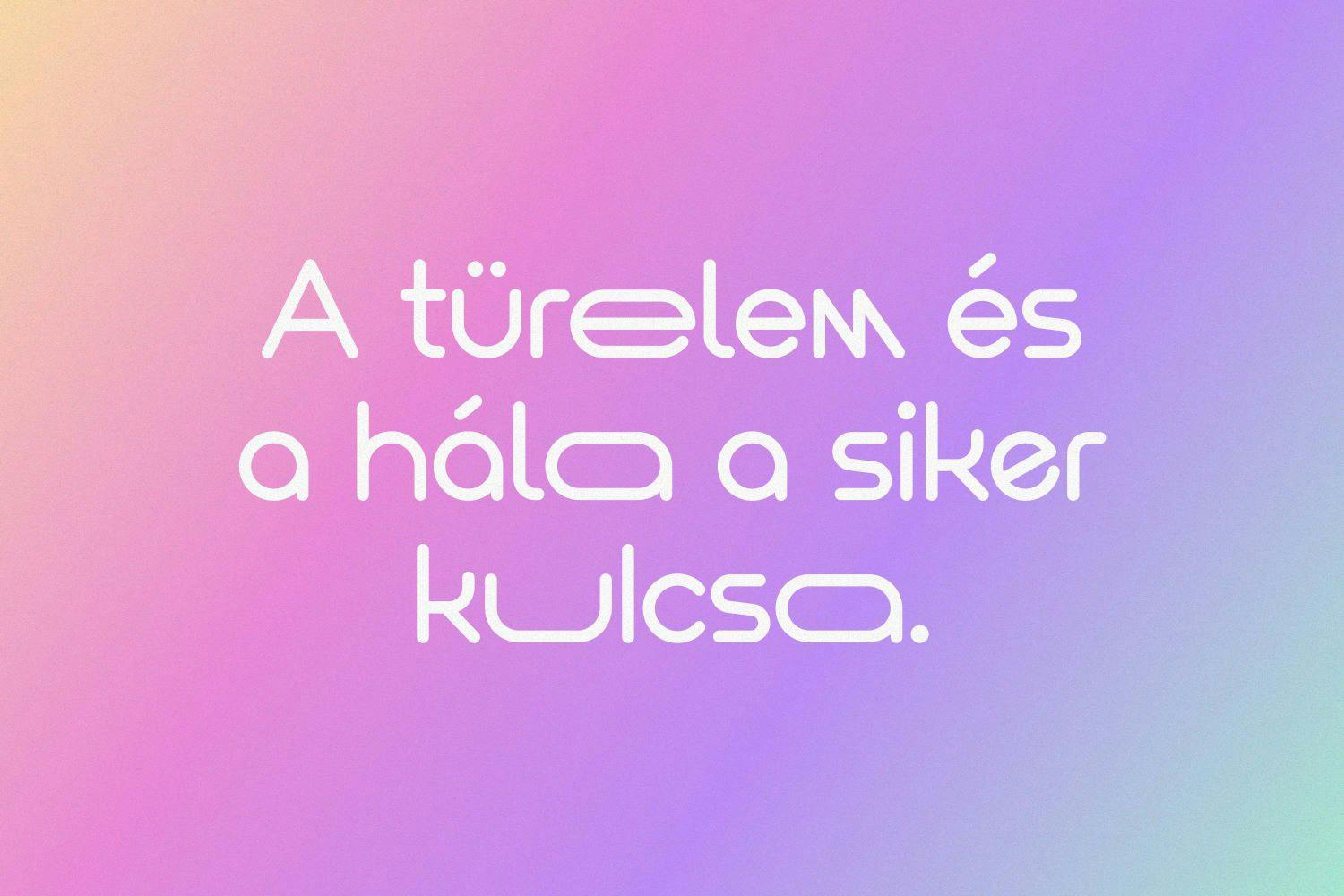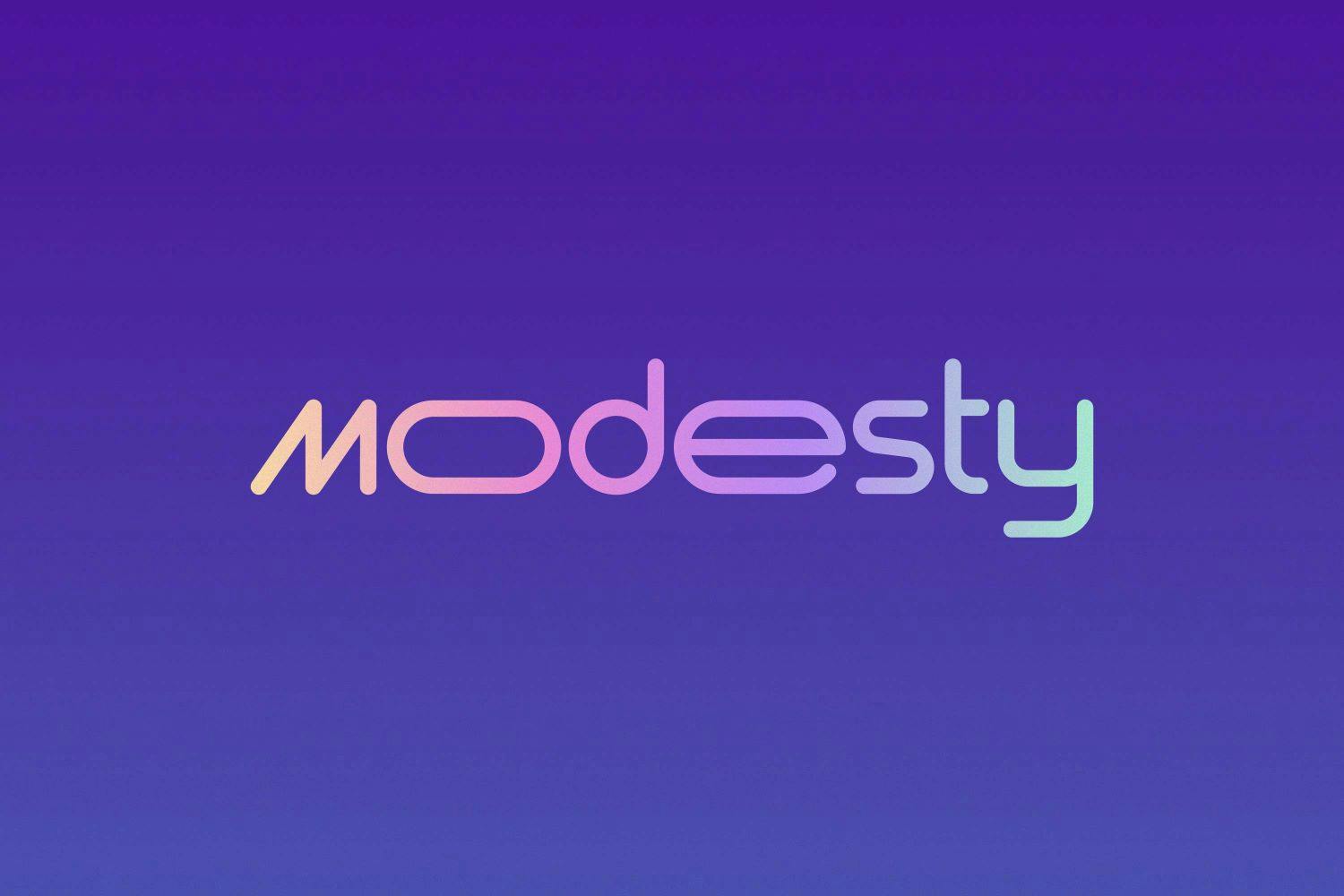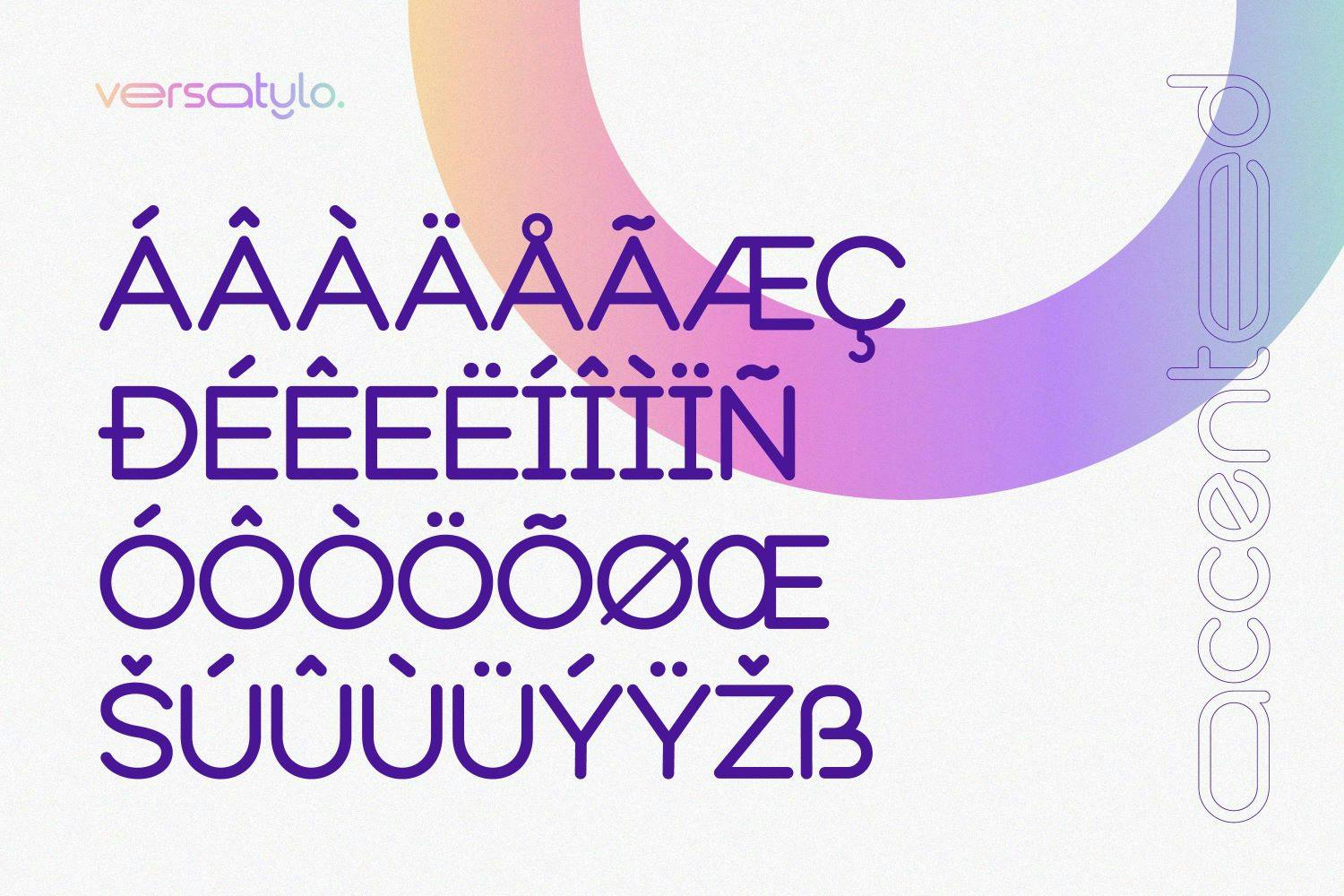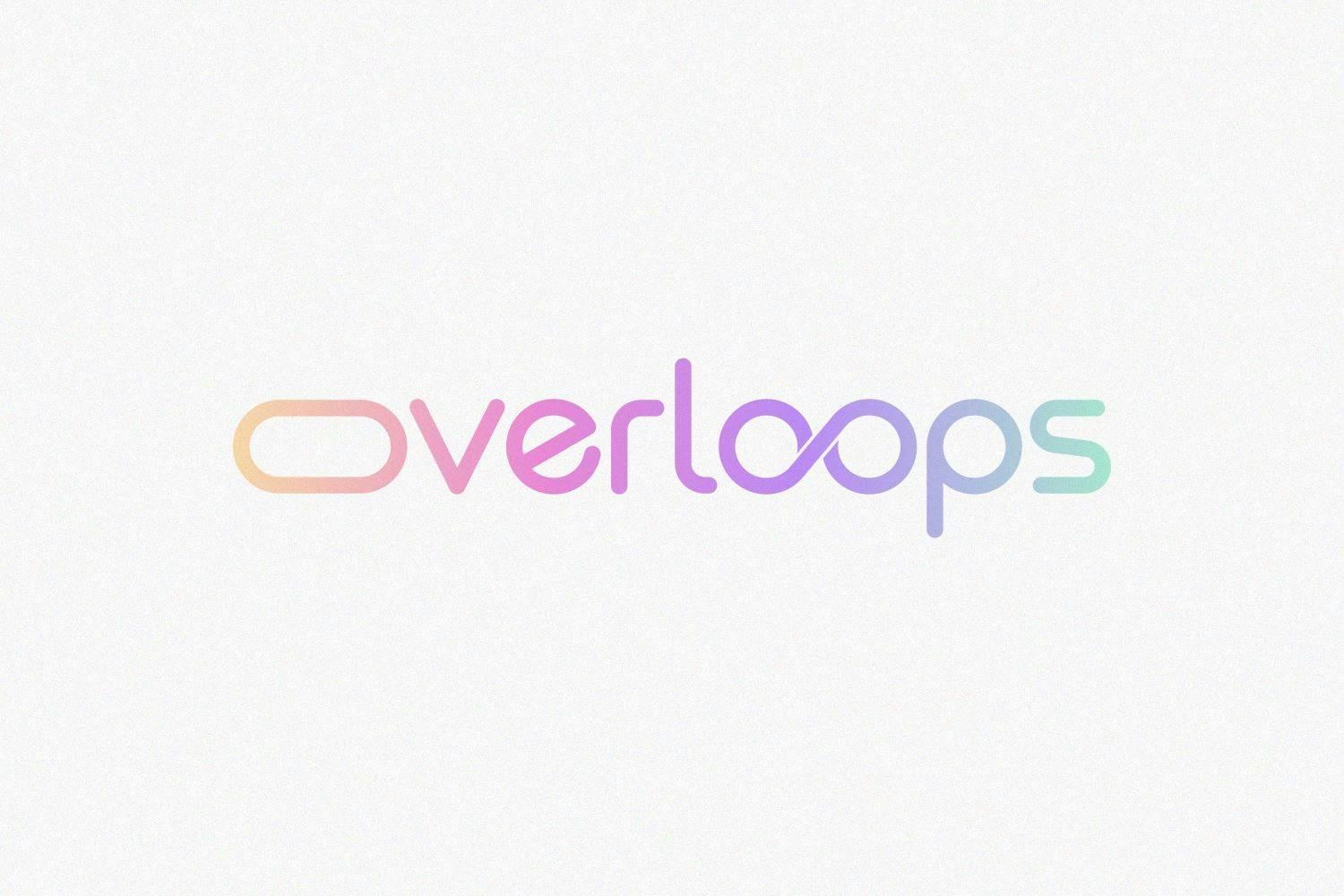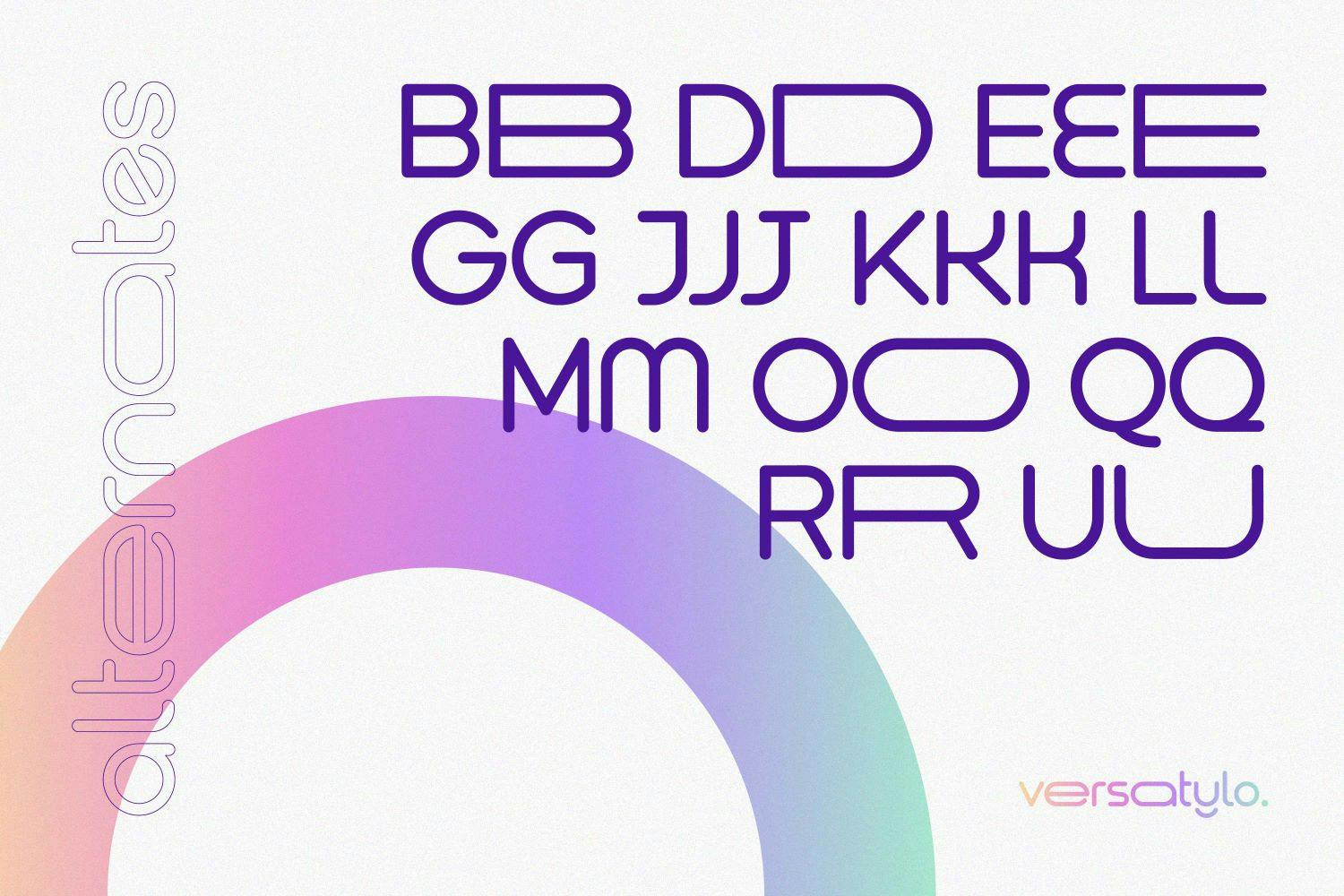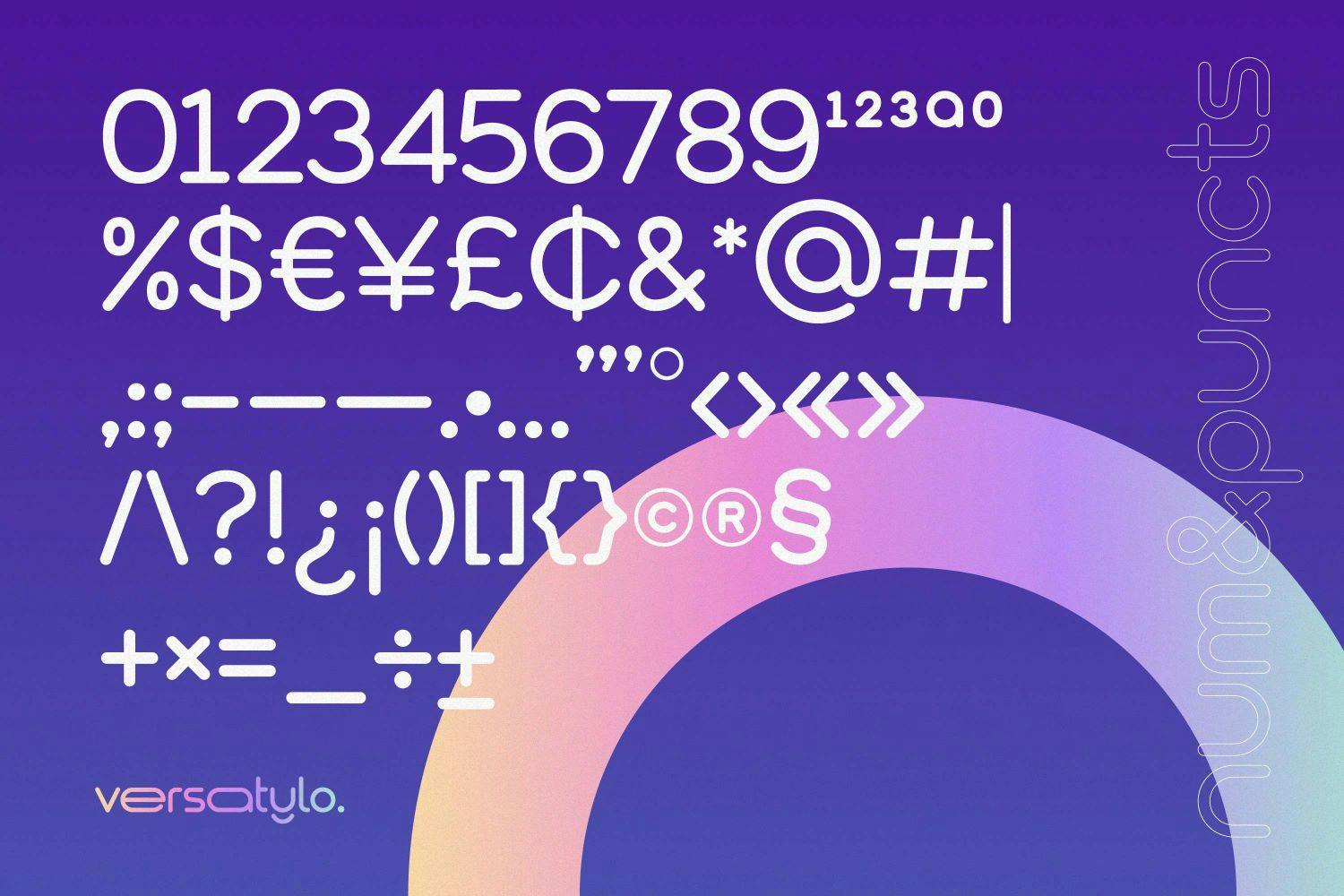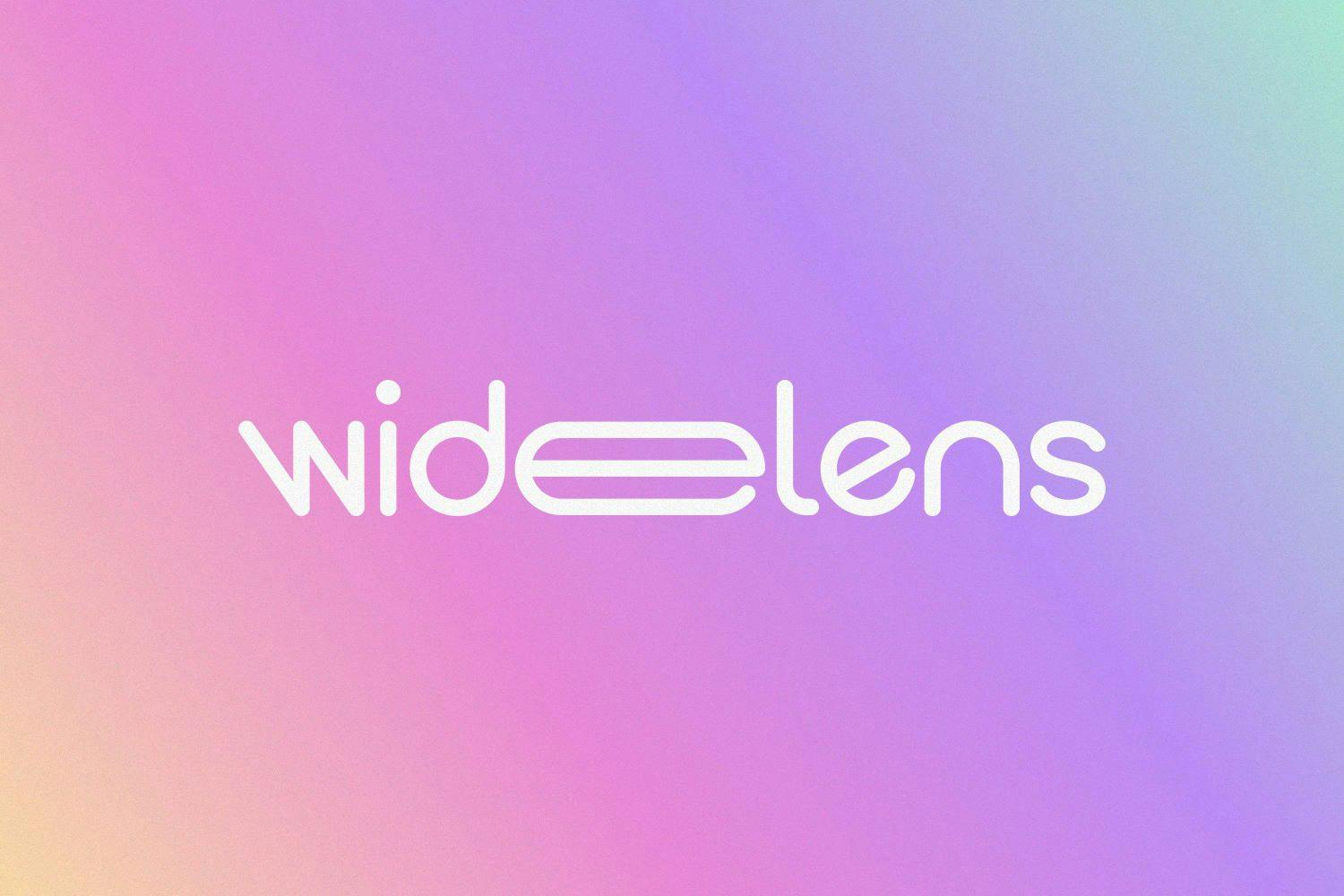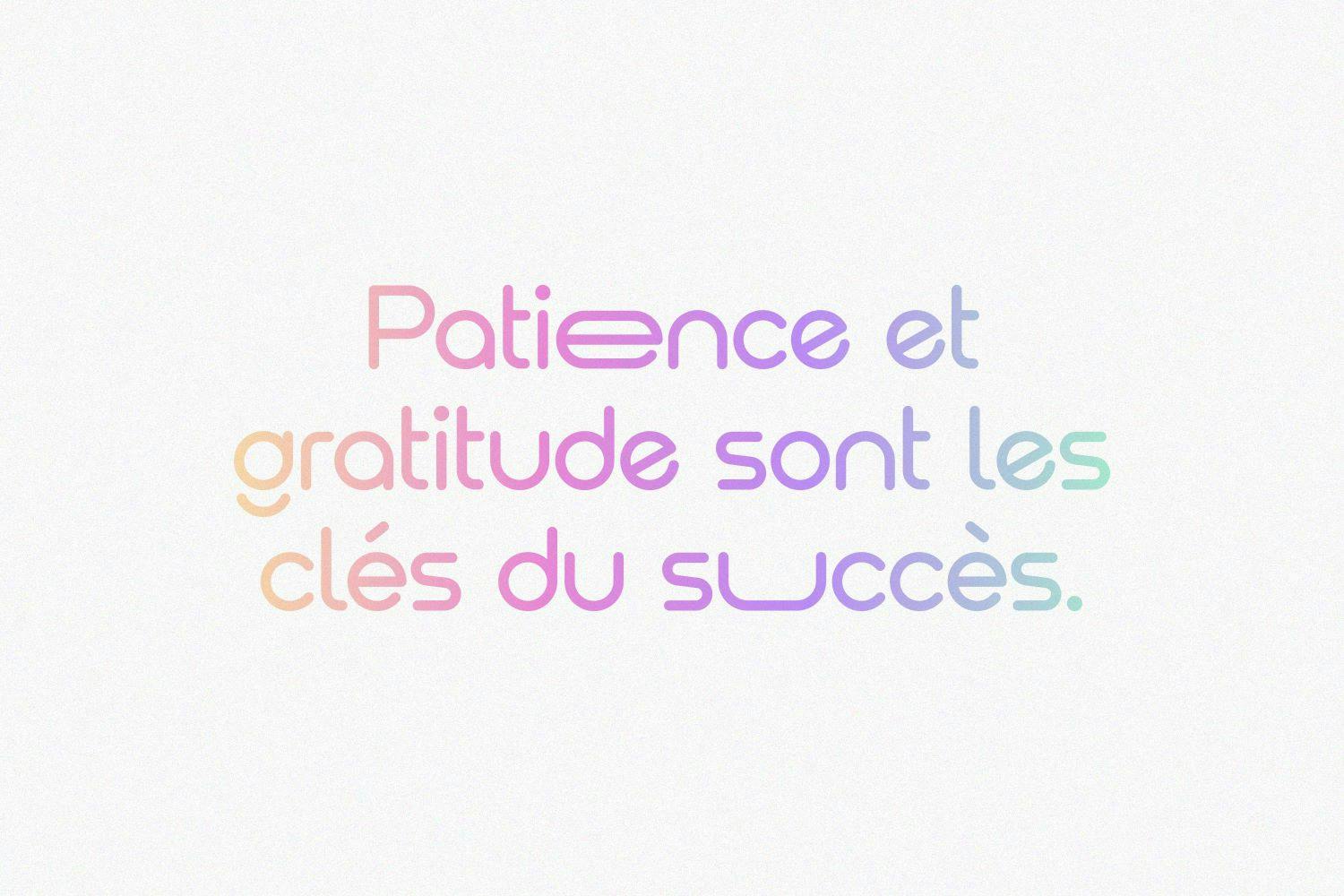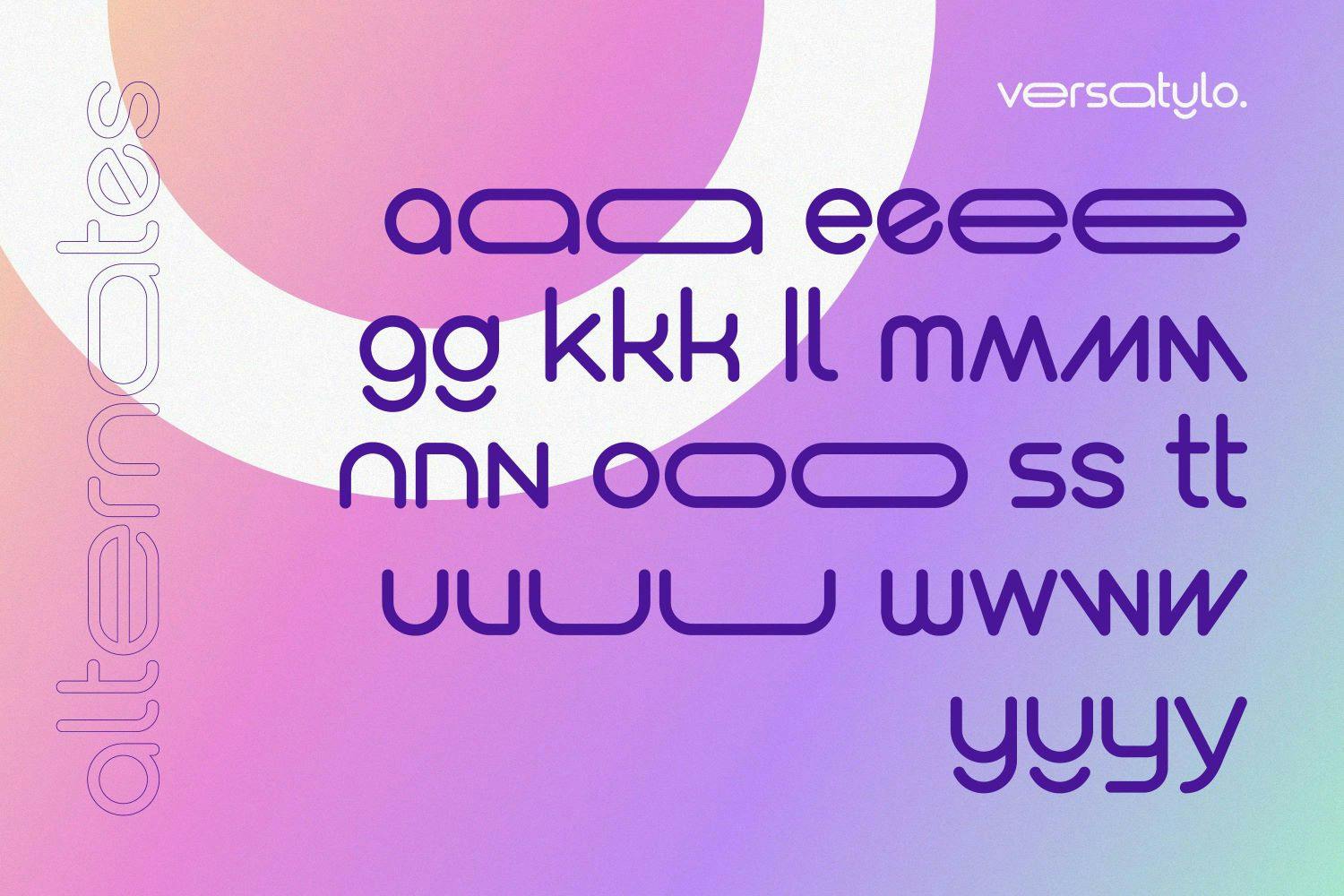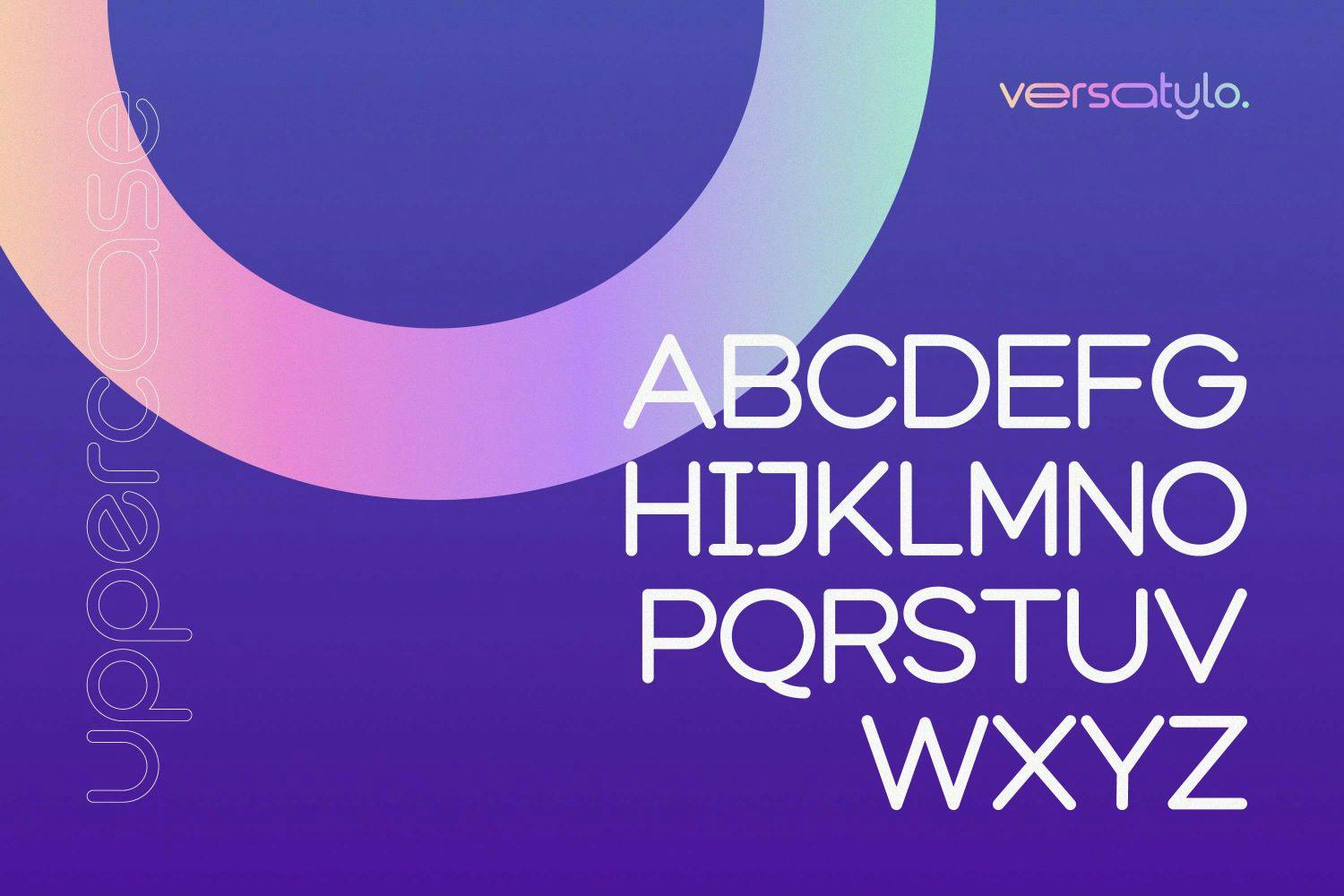
فونت Versatylo یک فونت بسیار قوی و برجسته برای برندینگ است که در هر شرکتی که میخواهد تصویر خود را مدرن و با تکنولوژی بالا جلوه دهد، قابل استفاده میباشد. با استفاده از این فونت، لوگوی خاص خود را طراحی کنید.
ویژگیهای فونت
- اکسنتهای اضافی
- پشتیبانی از ۶۶ زبان
- کرنینگ
- جایگزینها
- لیگاتورها